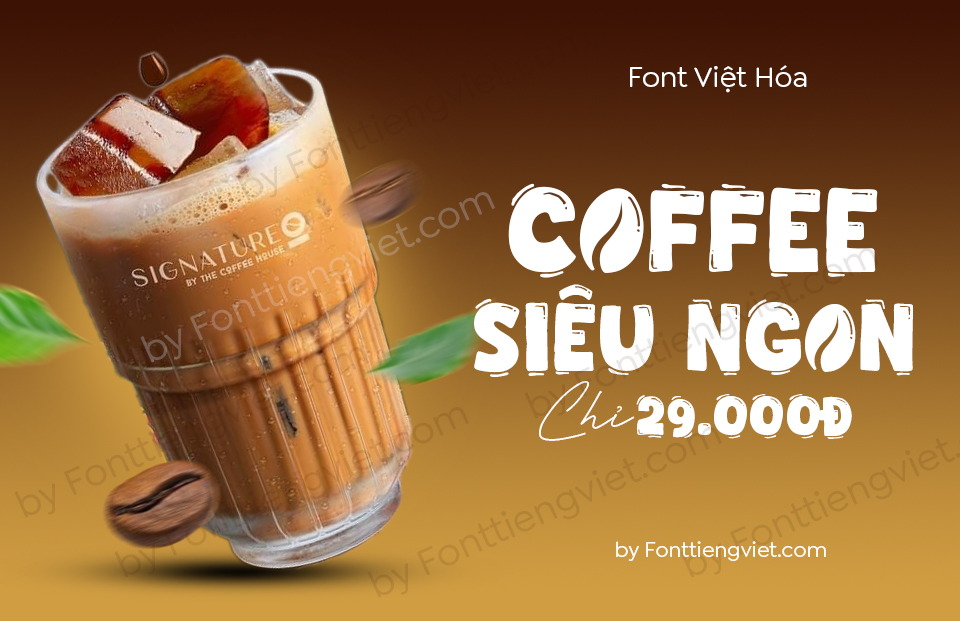
Font Việt hóa 1FTV VIP Coffee Town
Giới thiệu về Font Việt hóa 1FTV VIP Coffee Town
Trong thế giới thiết kế đồ họa hiện đại, việc lựa chọn một bộ Font Miễn Phí chất lượng luôn là ưu tiên hàng đầu của các nhà sáng tạo. Font Việt hóa 1FTV VIP Coffee Town nổi lên như một lựa chọn hoàn hảo dành cho những ai yêu thích phong cách cổ điển xen lẫn nét hiện đại. Đây là bộ font được tinh chỉnh kỹ lưỡng về dấu tiếng Việt, giúp người dùng dễ dàng ứng dụng vào các dự án truyền thông mà không lo lỗi hiển thị. Với đường nét thanh thoát và bố cục cân đối, bộ font này mang đến cảm giác ấm áp, gần gũi như không gian của một quán cà phê sang trọng.
Đặc điểm nổi bật của Font Việt hóa 1FTV VIP Coffee Town
Phong cách thiết kế độc đáo
Bộ Font Việt hóa 1FTV VIP Coffee Town sở hữu cấu trúc chữ độc đáo với những đường cong mềm mại nhưng vẫn giữ được sự chắc chắn. Điểm mạnh của bộ font này là khả năng tương thích cao với nhiều phần mềm thiết kế như Photoshop, Canva hay Illustrator. Sự tỉ mỉ trong quá trình Việt hóa giúp các ký tự đặc biệt của tiếng Việt trở nên hài hòa hơn, tạo nên sự đồng nhất cho toàn bộ văn bản.
Tính ứng dụng đa dạng trong giáo dục và đời sống
Không chỉ giới hạn trong ngành quảng cáo, bộ font này còn rất phù hợp cho học sinh và giáo viên khi thiết kế bài giảng hoặc làm báo cáo dự án. Nhờ tính dễ đọc và thẩm mỹ cao, nó giúp nội dung trở nên thu hút và chuyên nghiệp hơn. Bạn có thể sử dụng font để làm tiêu đề sách, thiệp mời hoặc các ấn phẩm trang trí trường học một cách linh hoạt.